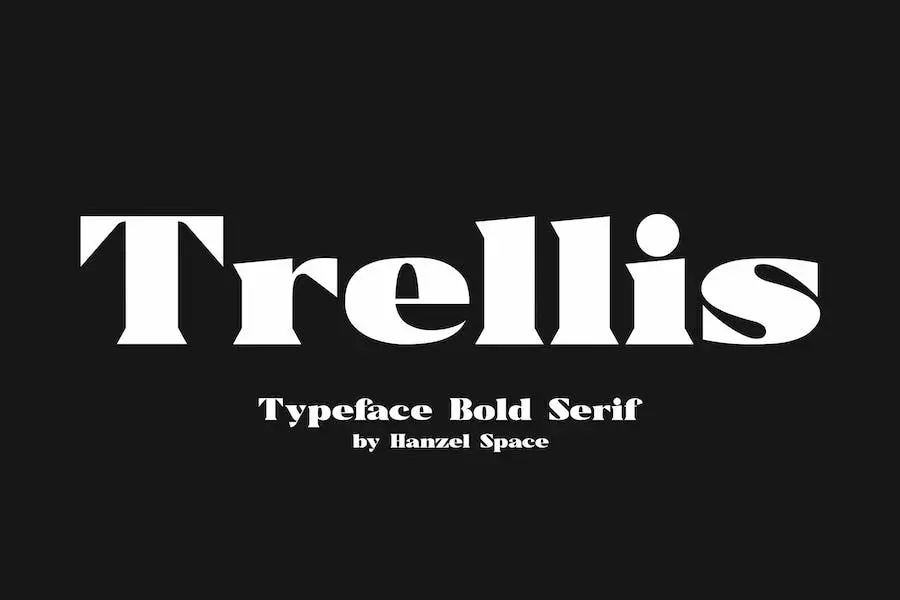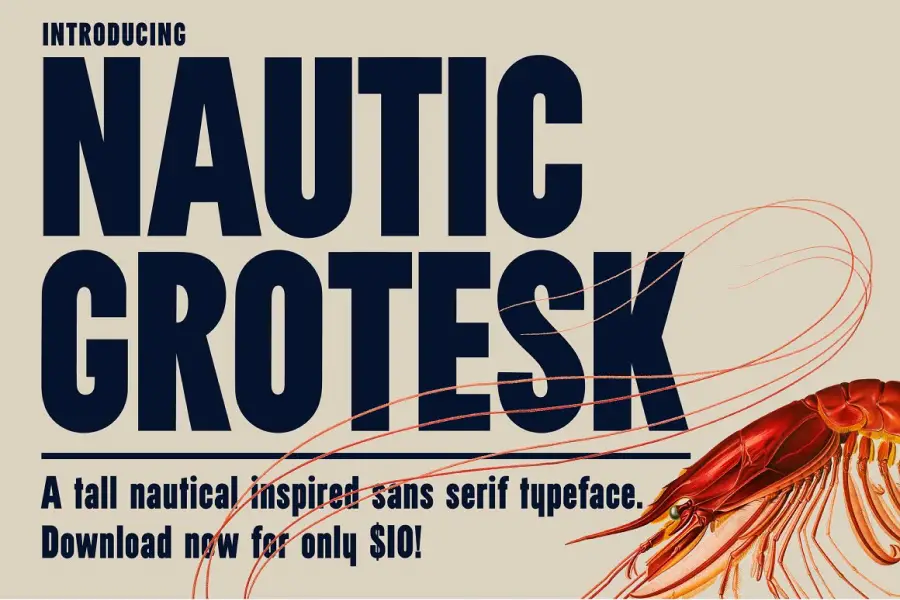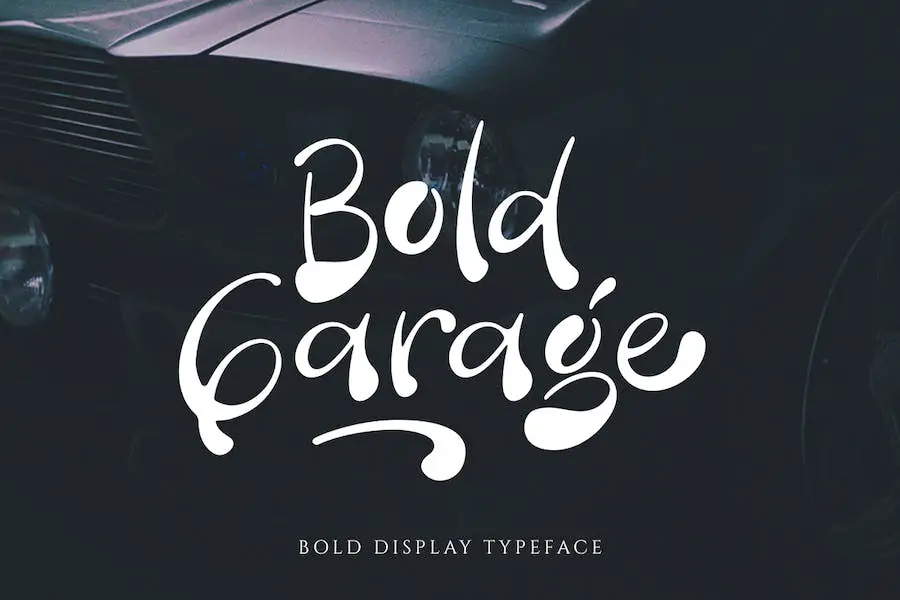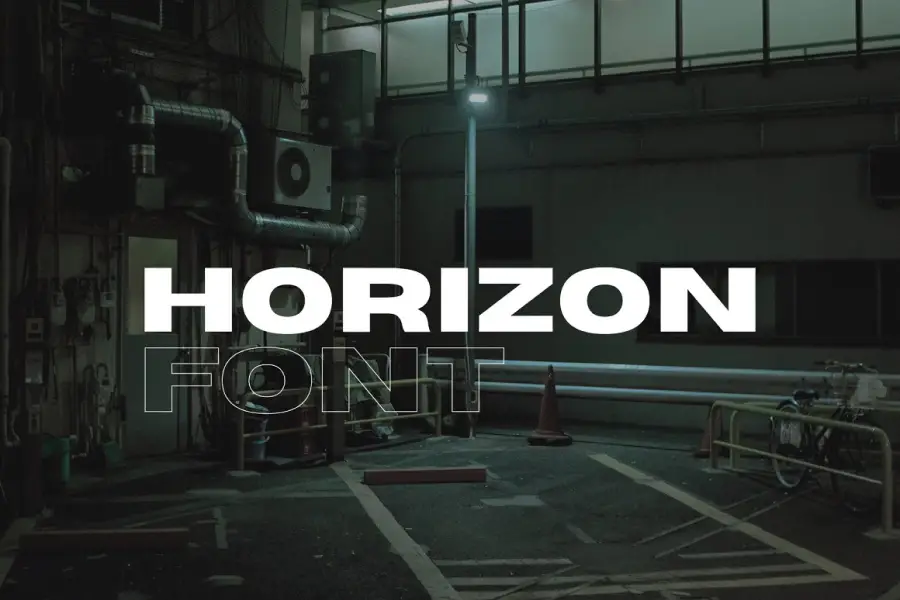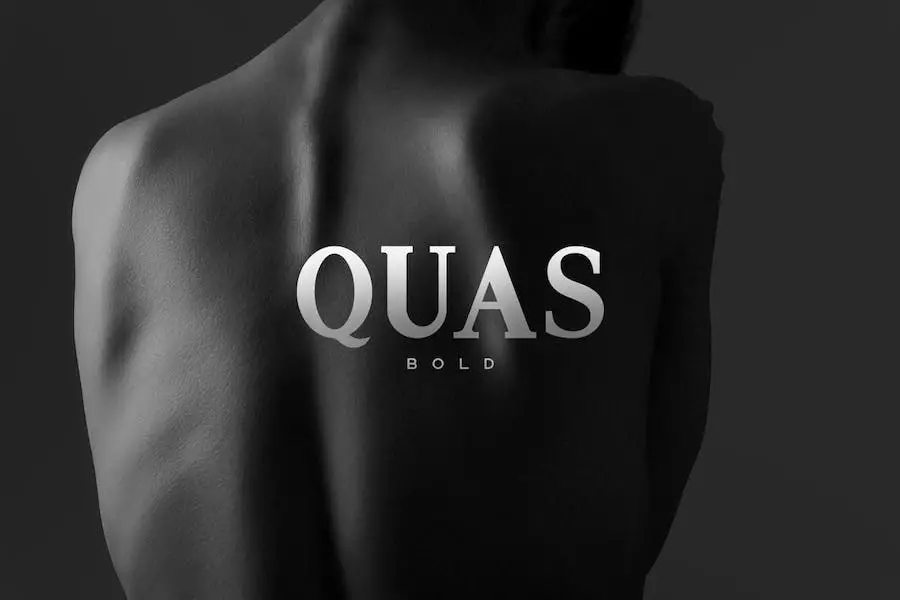
24 melhores fontes em negrito 2023 (grátis e profissionais)
Publicados: 2023-04-28Você já se viu lutando para escolher a fonte certa para o seu projeto? Com tantas opções disponíveis, pode ser difícil decidir qual delas causará o maior impacto. É aí que entra nosso post no blog sobre as “24 Melhores Fontes em Negrito”!
Fizemos a pesquisa e compilamos uma lista das fontes em negrito mais eficazes que certamente darão ao seu trabalho o toque extra de que ele precisa.
Neste artigo, discutiremos as 24 principais fontes em negrito que são perfeitas para fazer uma declaração. Fontes em negrito são uma ótima maneira de enfatizar informações importantes e chamar a atenção para pontos-chave em seu design, seja para um site, pôster ou brochura.
De acordo com estudos, o uso de fontes em negrito nos títulos pode melhorar a legibilidade e as taxas de retenção dos leitores.
Seja você um designer gráfico, profissional de marketing ou simplesmente alguém que deseja aprimorar seus projetos criativos, nossa lista de fontes em negrito o cobre. Continue lendo para aprender sobre as características únicas de cada fonte e como elas podem elevar seus designs.
Melhores fontes premium em negrito e pesadas
Você sabia que, de acordo com um estudo recente da Adobe, usar uma fonte exclusiva pode aumentar o reconhecimento da marca em até 12%? Portanto, nossa lista com curadoria de fontes em negrito premium não apenas elevará seu jogo de design, mas também poderá aumentar a visibilidade de sua marca.
Sem mais delongas, vamos mergulhar em nossas principais escolhas para as melhores fontes em negrito premium que certamente farão seus designs se destacarem da multidão.
MARGARIDA
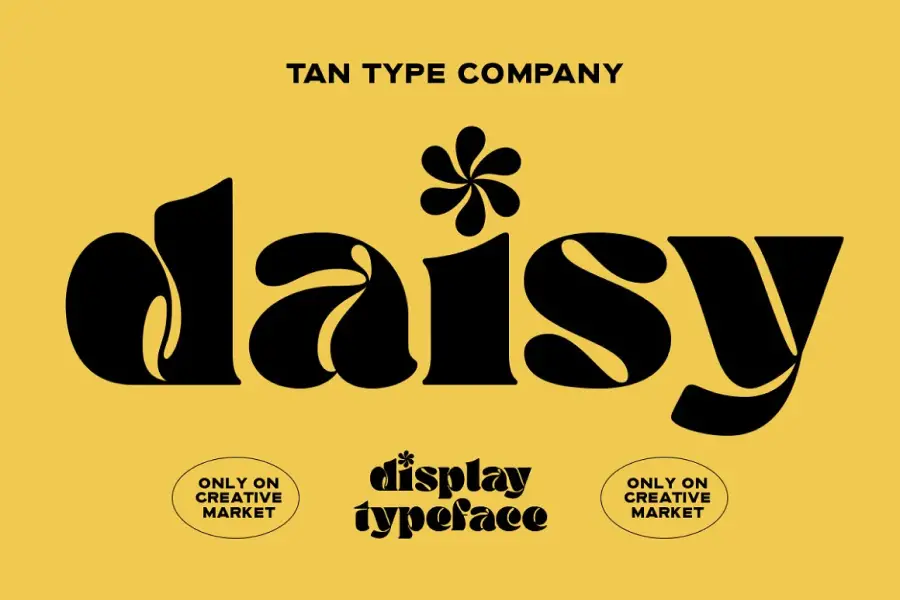
DAISY é um tipo de letra moderno e descolado que adicionará um toque retrô a qualquer projeto de design. Essa fonte grossa e ousada é cheia de personalidade e oferece muitas oportunidades para experimentação criativa.
Com seu charme peculiar, DAISY é perfeito para adicionar um toque de diversão aos seus designs. Esteja você criando fontes em negrito para logotipos, pôsteres ou gráficos de mídia social, esse tipo de letra divertido certamente fará uma declaração.
Uma das características de destaque da DAISY é a sua ousadia. Os traços grossos facilitam a leitura, mesmo em tamanhos menores, e o peso geral da fonte dá uma sensação de poder e presença. Além disso, as bordas arredondadas proporcionam uma sensação mais suave e acessível.
Aventi
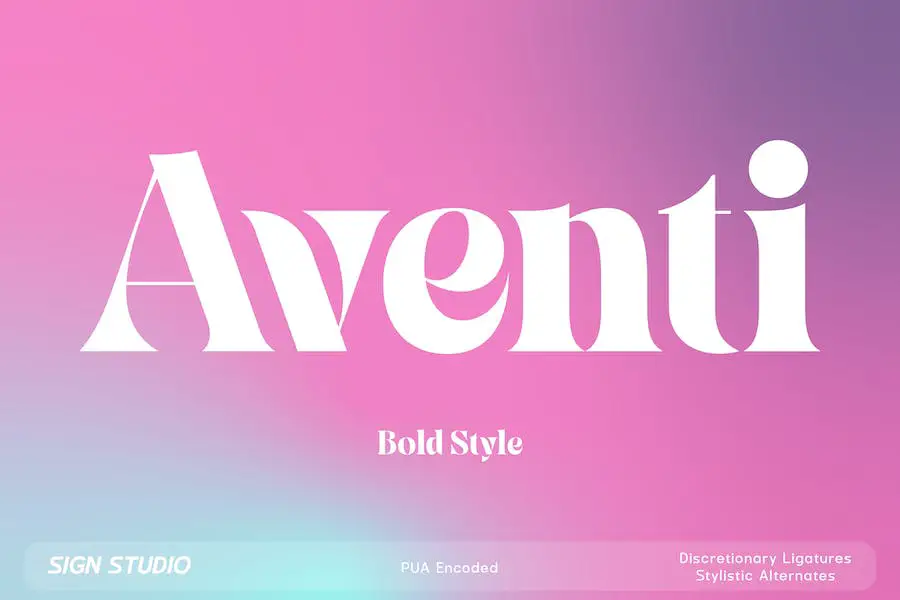
Aventi é uma elegante fonte serifada que vem com recursos exclusivos para aprimorar uma ampla gama de ideias de design. Com seu conjunto de alternativas estilísticas e ligaduras discricionárias, este tipo de letra oferece versatilidade excepcional para branding, rótulos, cartões e outros projetos de design.
Essa fonte também é codificada por PUA, o que permite acessar todos os glifos, caracteres alternativos e ligaduras com facilidade.
O conjunto de alternativas estilísticas da fonte inclui quatro letras (a, e, g, y), o que significa que você pode escolher entre diferentes designs para essas letras, encontrando o estilo perfeito para se adequar ao seu projeto.
CF Integral
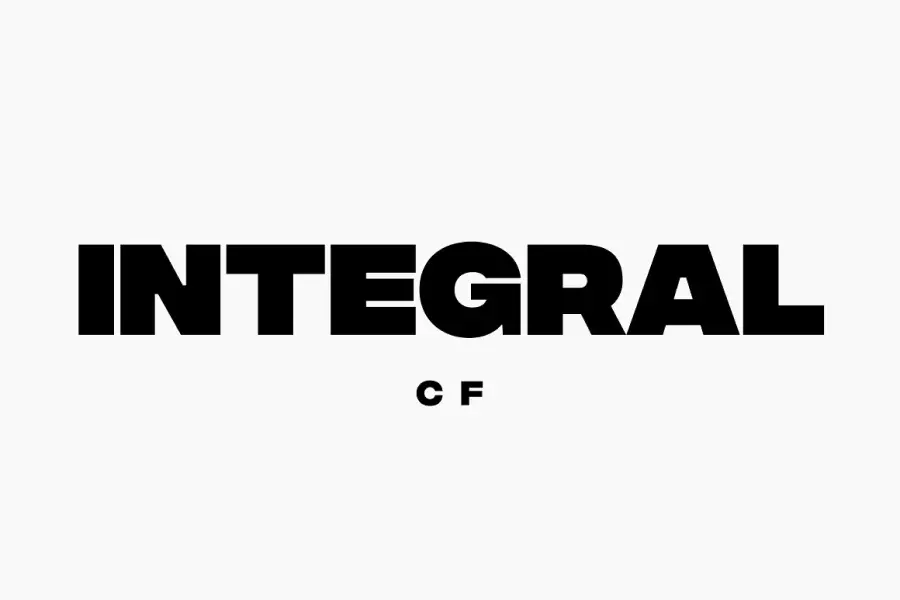
Integral CF é uma fonte que dá um soco. Com seis pesos diferentes para escolher, essa fonte é perfeita para qualquer projeto de design em que você queira fazer uma declaração ousada. Seja um pôster, gráfico de mídia social ou impressão de grande formato, o Integral CF certamente chamará a atenção de qualquer um que o vir.
Mas não se deixe enganar por suas linhas retas e sensação corporativa; há uma pitada de diversão escondida dentro de cada personagem. Isso dá ao Integral CF uma personalidade única que fará com que suas palavras se destaquem da multidão. E com sua voz forte, sua mensagem será ouvida alta e clara.
Arémico
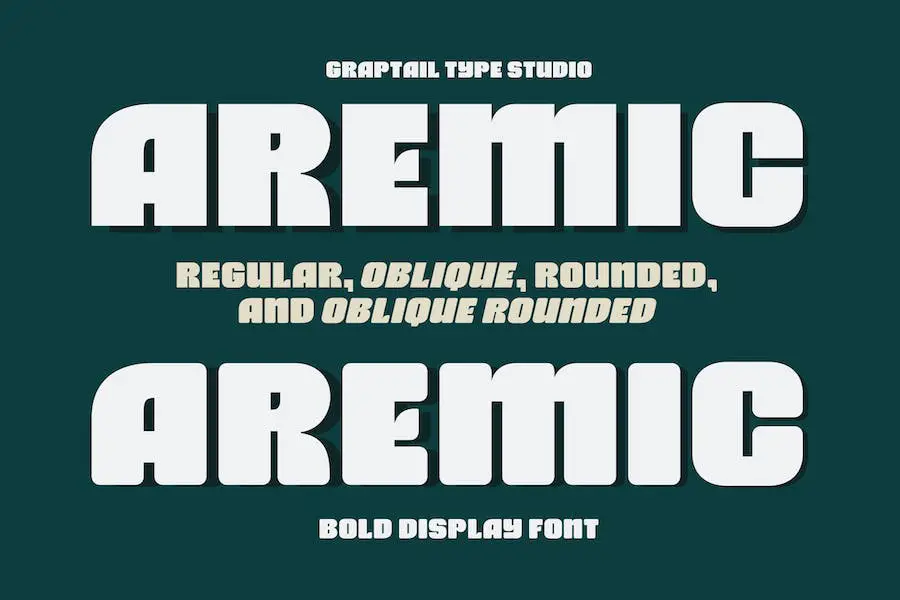
Aremic é uma fonte de exibição em negrito que vem em duas formas – regular e arredondada, incluindo oblíqua. Como o nome sugere, essa fonte é inspirada nas formas das letras dos pôsteres esportivos e é perfeitamente adequada para uso em logotipos, manchetes, sinalização, convites, cartões comemorativos, embalagens, moda, maquiagem, papelaria, romances e qualquer tipo de finalidade publicitária.
A ousadia da fonte Aremic a torna perfeita para criar designs impactantes que chamam a atenção do público. Essa fonte é especialmente adequada para logotipos e títulos, pois aprimora o apelo visual e destaca o texto. A fonte está disponível em duas formas, dando aos designers a flexibilidade de escolher a que melhor se adapta às suas necessidades de design.
Gunterz
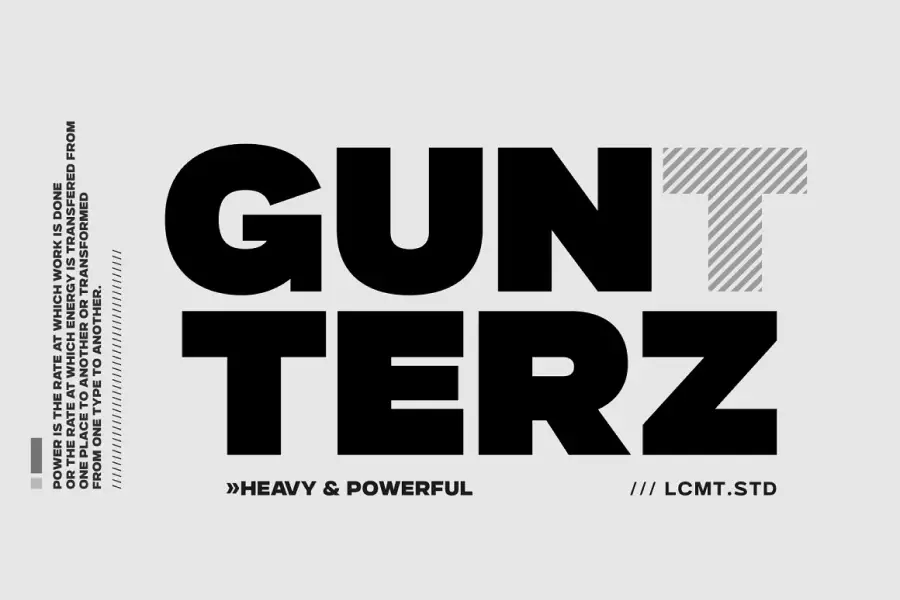
Gunterz é uma fonte sem serifa em letras maiúsculas que pode ajudar sua mensagem a se destacar com seu design arrojado e poderoso. Essa fonte vem em quatro pesos e seus itálicos correspondentes, tornando-a versátil para diversas necessidades.
Além disso, Gunterz possui recursos OpenType, incluindo alternativas estilísticas e um conjunto estilístico, para adicionar mais estilo à sua tipografia. Além disso, também suporta o idioma cirílico. Além disso, é ideal para Adobe Bold Fonts.